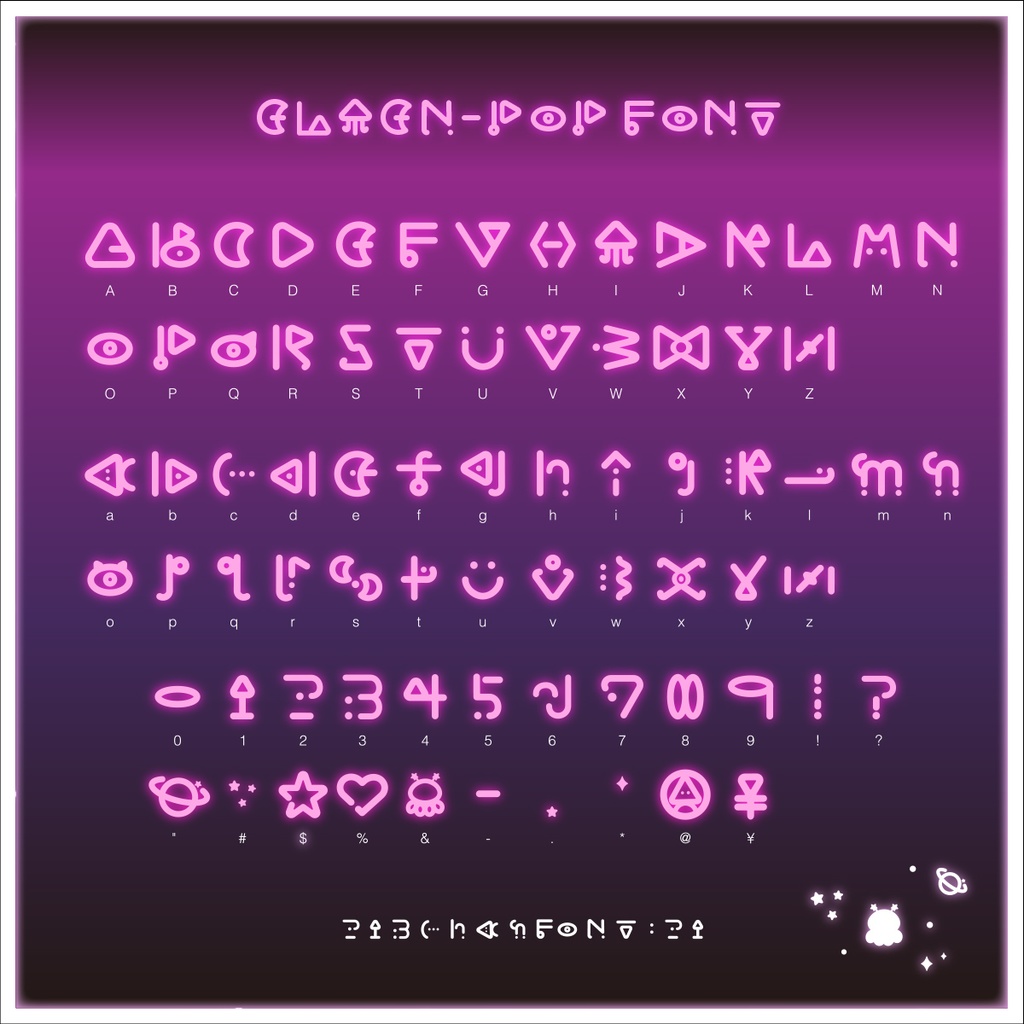
このエイリアン-ポップフォントは213ちゃんが作った21個目の商用可のフリーフォント(freefont)です。※ポップはポップ体の意味でつけています。 テレパシー代わりの宇宙語のフォントです。記号類もかわいいです! 読めないな…と思ったら、該当アルファベットを首を左に傾げてみると良いかもしれません。欧文のみだけど宇宙人VTuberさんにもオススメ☆ 通常:フリーダウンロード【商用可】 声援:有料DLで応援!¥100 【商用可】 印刷物・ゲームやWeb、YouTubeのサムネイルやタイトルデザインなどにいかがでしょうか? 基本フリーですが、当フォントを利用した制作物などを、SNSで教えてくれると励みになります。 制作時のお気に入りポイントをnoteで記事にしています。 https://note.com/sweet_2727/n/n4cc2f013eb3a ぜひ遊びにきてね!スキ!お待ちしています。 【収録内容】欧文(大小)・数字・記号 【Readme】フォントご使用上の注意 ・フォントの著作権は、213ちゃんに帰属します。 ・可愛がってくださるとうれしいです。 ・無断転載・再配布は堅くお断りいたします。 ・DLしたフォントに起因する損害は補償致しかねますので予めご了承ください。 ・使用する際の不明点はお問い合わせ先にご連絡ください。答えられる範囲でお返事いたします。 英文 This font (213chan font) is a free OpenType font that can be used for commercial and personal web and print designs. Please take care of me. Font copyright belongs to 213chan. Unauthorized reproduction, redistribution, resale, and trademark registration of logos created using fonts is strictly prohibited. Please note that we cannot compensate for damage caused by DL fonts. Please note that we do not provide support regarding installation or usage.